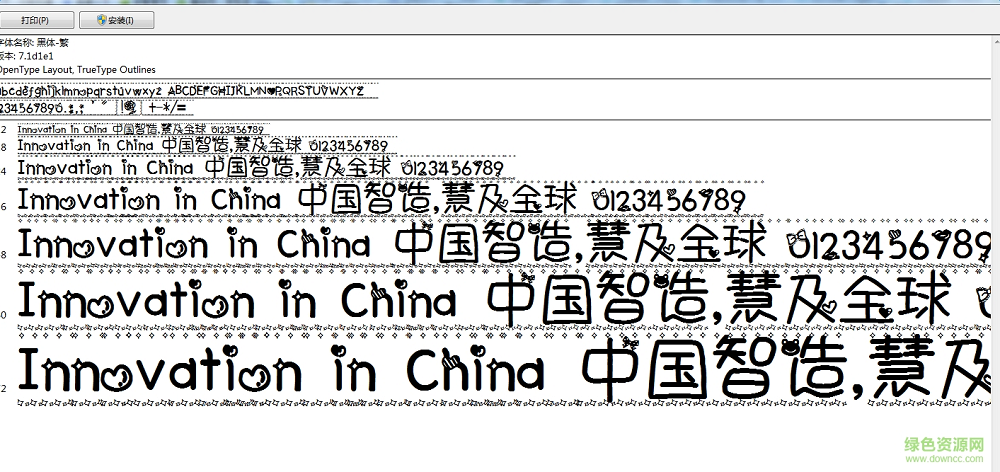
若隱若現(xiàn)字體是一款用于戀愛設(shè)計(jì)方面的字體,好似愛情若隱若離,虛幻縹緲,隨性而為,多用于文字排版、美工設(shè)計(jì)、廣告設(shè)計(jì)、海報(bào)設(shè)計(jì)等方面!需要的朋友趕緊來綠色資源網(wǎng)下載喲!
若隱若現(xiàn)字體清爽簡約,好似愛情甜甜蜜蜜,絲絲動(dòng)人。